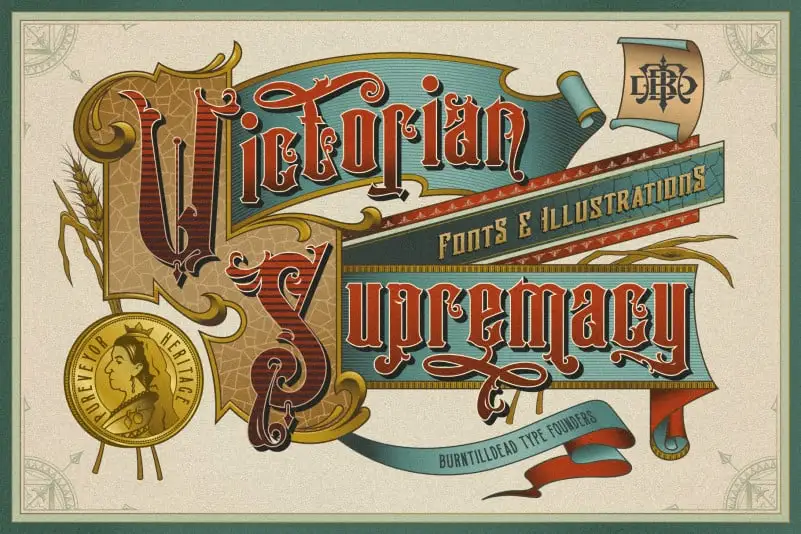
Victorian Supremacy Display Font – Fonte Grátis
Victorian Supremacy Display Font
Victorian Supremacy Display Font é uma obra-prima criada por Burntilldead para quem busca fontes que se destacam em ambientes visuais exigentes. Inspirada no auge do imperialismo britânico, este tipo de letra traz um toque de glamour e poder sem igual. Suas linhas fortes e detalhes precisos permitem criar designs impactantes nas campanhas publicitárias ou em anúncios impressionantes que exibem seu prestígio supremo. Ideal para aqueles que desejam dar um toque único à sua identidade visual, essa fonte oferece a oportunidade de construir uma imagem memorável. Seja você um designer gráfico experiente ou iniciante, este tipo de letra é perfeito para capturar a atenção e transmitir um forte impacto visual em qualquer ambiente.